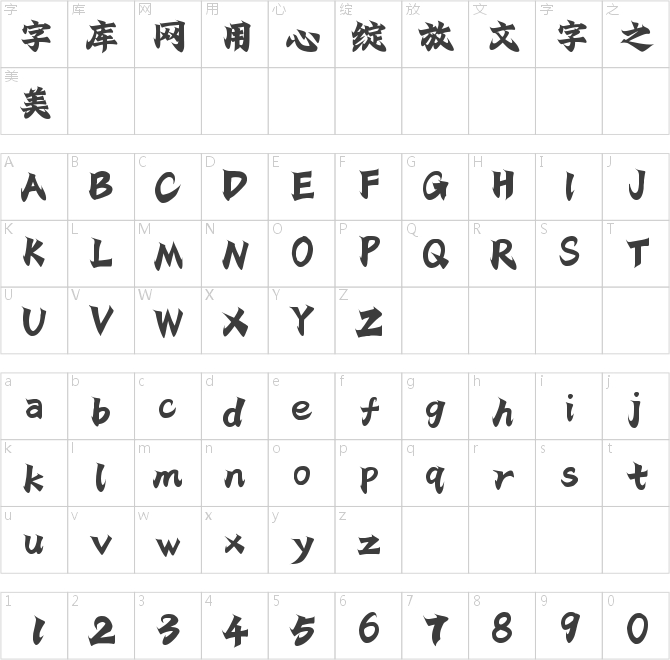
字體名稱: 字靈映月手書
字靈映月手書
字靈映月手書介紹
字靈映月手書字體字庫(kù)是一款讓人賞心悅目、百看不厭的中文字體,適合各類廣告和產(chǎn)品包裝設(shè)計(jì)應(yīng)用,字體大小8.35MB,格式為ttf字體,上傳用戶是woslxn,作者/版權(quán)方為字靈
字靈映月手書效果圖